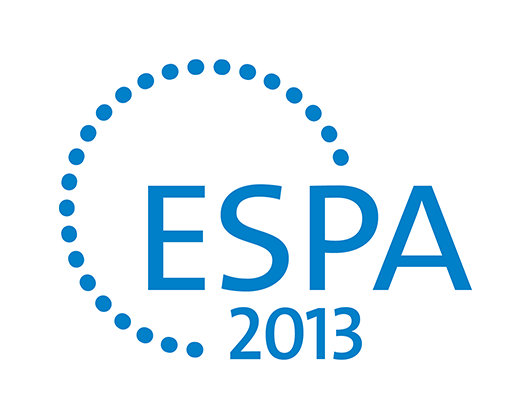
NOA – begleitender Font für Fließtext
Ich bin weiterhin sehr zufrieden mit der Kombo. Mal sehen was sich bei längeren Passagen tut.
Kleines Update:
Ich würde wegen des Wurststands kommen …  :bandit: Im Ernst: Für so geringe Textmengen ist sie durchaus brauchbar. Wobei du nur zweieinhalb Wörter in eine Zeile bekommst, das ist arg wenig. Ich plädiere immer noch für eine schmälere.
Was mich aber erschreckt, ist die sinnfreie Aufzählung von Schlagwörtern in Verbindung mit Wurststand und Hüpfburg. Da reißt’s dann die Schriftart auch nicht mehr raus ;-) Aber das ist ein ganz anderes Thema …  :-|
Die Apex Serif könnte noch gut/besser zur Noa passen.
Und wenn’s doch schmaler werden sollte, vielleicht mal Graublau Slab anschauen. Leider ordnet diese sich aufgrund ihres eigenwilligen g nur nicht so schön unter wie die Foro oder eben Apex.
Etwas dezenter bzw. unaufgeregter unter den schmalen Slabs wäre dann beispielsweise PTL Qugard Slab, FF Zine, PTL Manual Slab, FF Fago Correspondence Serif oder eben FF Unit … : )
Könnte mir vorstellen, dass dann die Fago in Deinem Fall am Besten passt.
PS.: Die Farbigkeit spricht mich nicht so an. Auch das Logo erscheint mir noch unausgereift, ebenso die Spationierung des URL, aber das nur am Rande ; )
Bertel, mag sein das das keinen Sinn macht, ist tatsächlich nur zum austesten. Ich kann es aber nachvollziehen, dass die energiespar Thematík beim Schlemmen mit anschließendem Hüpfen belastend wirken kann ;)
R::bert, SEHR reichhaltig, danke. Ich muss aber zugeben, dass ich gar nicht die Mittel habe, diese schönen Fonts auszuprobieren, da bin ich dann notgedrungen pragmatisch.
Hast du Lust näher über das Logo zu reden? Da würde ich gerne etwas dran verbessern.
Ich wollte durch die Perspektive einen "Weg weisen" und die Bildmarke soll "runterdrehen" symbolisieren.
Und du spationierst im ernst jede URL? Ich fürchte, dazu fehlt mir die Ausdauer.
Farbigkeit, tja. Da wird man wohl nie jedermanns Geschmack treffen können.
Man kann natürlich nicht jede URL in Fließtexten spationieren, aber, wenn diese so dominant, logomäßig dargestellt ist, tut das schon not. Auch auf Visitenkarten/Geschäftspapier lohnt sich das (genauso wie bei E-Mail-Adressen).
… näher über das Logo zu reden? Da würde ich gerne etwas dran verbessern. Ich wollte durch die Perspektive einen "Weg weisen" und die Bildmarke soll "runterdrehen" symbolisieren.
Wie bei der Schrift bin ich auch hier der Meinung, dass das Logo das nicht leisten kann. Das Logo soll mit Aussagen aufgeladen werden, die erläutert werden müssten, es aber nicht werden. Deine Gedanken wird kein Betrachter haben, weil er sich gar nicht so intensiv mit dem Logo auseinandersetzt.
Ich befürchte, dass du mit dem perspektivischen Logo eine "Pflichtgestaltung" festlegst, nämlich den Winkel. Ohne diesen wird das Logo nicht funktionieren. In meinen Augen eine unnötige Einschränkung.
Deinen ursprünglichen Vorschlag fand ich gar nicht schlecht — klar, professionell, eigenständig.
Zu dem Logo würden mich brennend weitere Meinungen interessieren.
Das das, was ich mir dabei denke nicht erkannt wird, ist für mich i.O., aber
zumindest führt es zu einer gewissen Prägnanz in der Optik, ohne willkürlich zu sein.
Ist die Ursprungsversion nicht zu einfach? Durch die Noa hat es was, stimmt auch irgendwie ..
Ich habe nun übrigens noch die FF Unit Slab zur Verfügung, die mir, nicht nur bei diesem Thema, gute Dienste erweisen wird. Sie hat mich einfach vom Gefühl her überzeugt, ohne das ich dafür jetzt nähere Gründe nennen könnte.
ich finde, die kombination mit der foro passt – besser als die apex serif.
Mir schienen die Formen der Apex noch ein klein wenig »innovativer/moderner« zu wirken und auch in ihrer Gestaltung (beispielsweise e) gut oder eben besser zur Noa zu passen. Dass die Apex auch ein eigener Charakter ist, bleibt unbestritten. Aber vielleicht wäre das in dieser Anwendung zu verkraften gewesen.
Oh … wollte Dich mit meinen Gedanken nicht überrumpeln. Mir schien nur, Du seist recht typointeressiert wenn nicht sogar -begeistert. Da dachte ich, ein kleiner Ausflug zu weiteren Familien könnte inspirieren. Vielleicht kannst Du die später mal gebrauchen ; )
Doch doch, ich fand das sehr gut und hab mir das auch sehr genau angeguckt. Nur kann ich die ja nicht einfach probeladen.
Nee! Ich halte es da wie Schnitzel. Da die Noa aber schon etwas »speziell« ist, scheint sie mir auch etwas mehr Fingerspitzen-Gefühl zu brauchen.
Vorab, die Richtung habe ich so gewählt, da wir ja von links nach rechts lesen und so auch das Logo interpretieren. Links Ist, rechts Soll.
Den Schwung aus Punkten zu setzen finde ich einen bemerkenswerten Ansatz, denn so ließe sich im späterem Corporate Design eine schöne Form für zB Fotos herleiten.